2023 年 15 种最佳草图字体(免费和付费)
已发表: 2023-09-08您是一名想要提升项目设计的平面设计师吗? 您是否正在努力寻找一款完美的字体来增添额外的创造力和独特性? 好吧,别再看了! 我
在这篇博文中,我们将深入研究草图字体的世界,并展示 2023 年 15 种最佳选择,包括免费和付费字体。 但在我们深入探讨之前,您可能想知道,草图字体到底是什么以及为什么应该考虑使用它们?
草图字体是一种模仿草图或涂鸦的手绘美感的字体。 它们为任何设计项目增添了一丝奇思妙想、个性和创造力。
无论您是在设计徽标、包装设计还是网站布局,草图字体都可以立即使您的作品脱颖而出。
现在,让我们来谈谈是什么让这篇博文真正令人兴奋——2023 年 15 种最佳草图字体。在本文中,您将找到一个精心策划的列表,其中包括免费和高级选项。
我们知道,作为一名平面设计师,您可能会受到预算限制,因此我们提供了一系列选项来满足每个人的需求和偏好。
在这篇博文中,我们将向您简要介绍每种字体、其主要功能以及如何在不同的设计项目中最好地利用它。
因此,无论您是初学者设计师还是经验丰富的专业人士,本文都是您寻找完美草图字体以将您的项目提升到新水平的首选资源。 因此,事不宜迟,让我们直接开始探索草图字体的奇妙世界!
最佳高级素描字体
希望将您的平面设计项目提升到一个新的水平? 我们精心挑选的最佳优质草图字体就是您的最佳选择。 准备好开启创意世界并增强设计的视觉吸引力。
不要错过探索这些令人难以置信的字体并彻底改变您的设计游戏的机会!
素描师
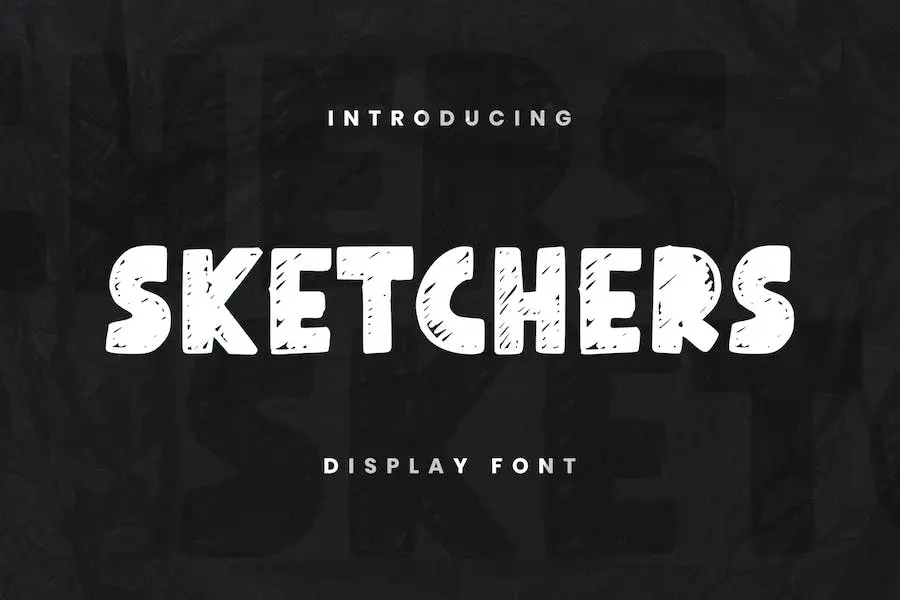
Sketchers 是一种名为“Presenting It”的字体,它提供了一系列功能和样式来增强您的设计项目。 该字体非常适合徽标、品牌、书籍、T 恤、杂志布局、问候语和标题,用途广泛,可适应各种设计需求。
借助大写和小写字母、数字和标点符号、多语言支持和 OpenType 功能,您有无数的选择来创建令人惊叹的设计。
另外,您还可以将其与其他字体混合以添加互补的感觉。 使用 Sketchers 为您的项目赋予独特且专业的外观。
特威克
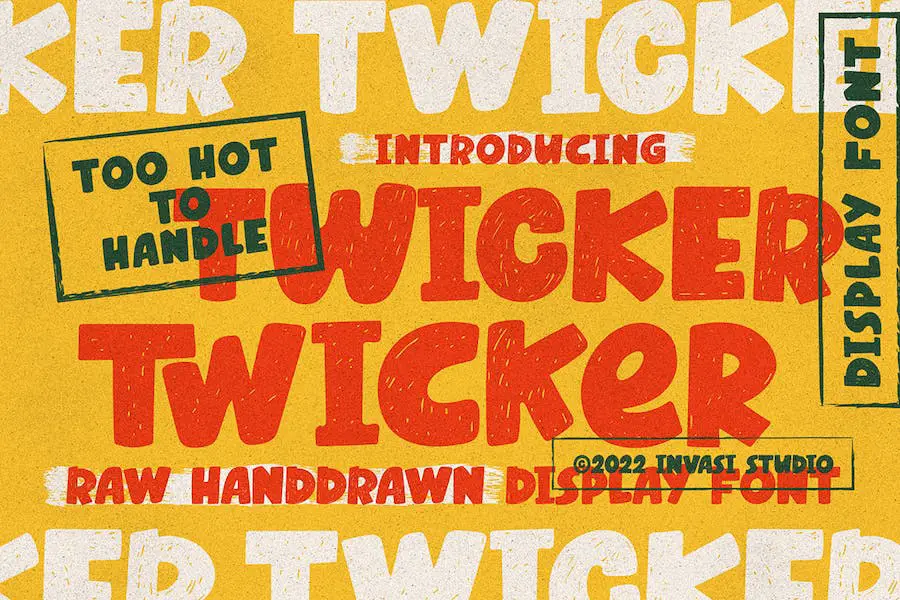
Twicker 是一种具有有趣的草图、纹理和垃圾阴影风格的字体。 其细节字形以迷人的气泡形状出现,赋予其独特的手绘外观,极具吸引力。
凭借各种替代字形和连字,您有很多选项来自定义您的项目。 无论是品牌项目还是包装,Twicker 都是增添俏皮感的完美选择。
粉笔时间
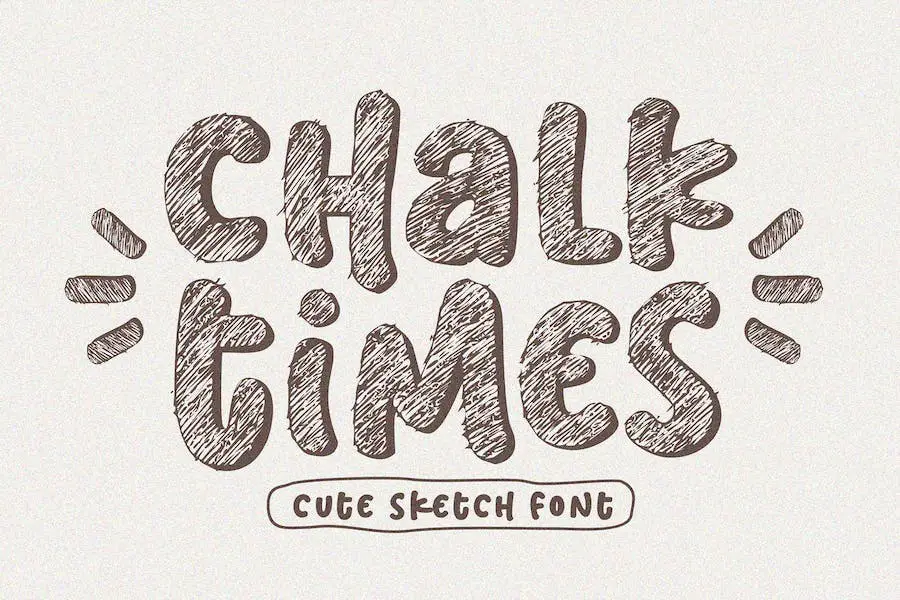
Chalk Times 是一种可爱、活泼、友好的轮廓显示字体,具有铅笔素描风格。 其自然而独特的设计使其非常适合各种项目。 通过 Chalk Times,您可以享受乐趣并探索这种美丽字体的无限可能性。
草图
Sketchup 是一种令人难以置信的字体,它将把您的设计提升到一个新的水平。 凭借其独特的草图显示板风格,它可以为您的徽标、标题、海报、徽章、T 恤等增添一抹个性。
受到装饰艺术和建筑运动的启发,这种字体为您的项目带来了美丽而有趣的元素。
无论您是要创建证书、帖子、徽标、海报、标签还是其他任何内容,Sketchup 都是让您的设计脱颖而出的完美选择。
艾洛迪
Elodie 是一种全大写字体,具有独特而古怪的字符。 该字体是使用毛笔创建的,给人一种手写和有机的感觉。 它非常适合标题、简短引言、产品名称等。
要为常规文本添加一丝奇思妙想,只需使用小写字母即可。 但如果您想让您的写作更加特别,请利用大写部分来实现那些独一无二的怪癖。
此外,Elodie 还为多种语言提供多语言支持,包括西欧、中欧和东欧语言。
素描手绘
Sketch Hand Drawn 是一款有趣的原创手写字体,能够让任何 DIY 项目变得栩栩如生。 凭借其华丽而独特的设计,这种字体非常适合希望为其项目添加个人风格的图形设计师。
无论您是在制作海报、徽标还是网站,素描手绘都一定会增强整体设计并使其脱颖而出。 其手工制作的外观增添了一种真实感和创造力,为您的作品带来独一无二的魅力。
使用 Sketch Hand Drawn 字体给您的项目带来新鲜和艺术的感觉。
萨利塔素描
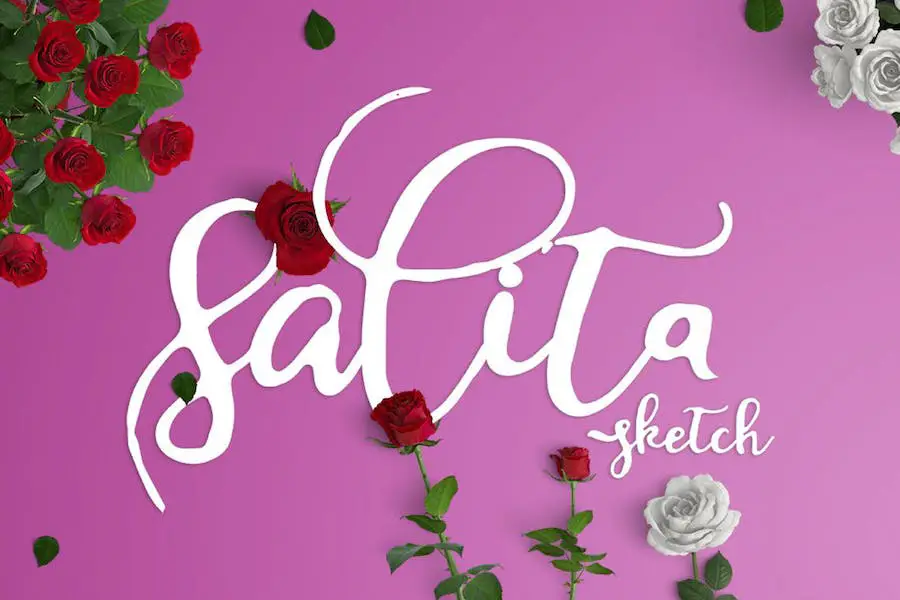
Salita Sketch 是一种为您的设计项目带来新鲜和现代气息的字体。 该字体拥有超过 340 个字形,提供了广泛的替代字符,包括花体和风格集,为您提供了大量的选项来增强您的设计。
Salita Sketch 的独特之处在于其手工书法风格和装饰字符,为您的作品增添优雅和俏皮的元素。
粉笔素描
Chalk Sketch 是一款很棒的显示字体,可为任何针对儿童的设计增添创意。 它用途广泛,可用于各种项目,如品牌、标志设计、T 恤、书籍封面等。
这种字体非常适合社交媒体帖子、广告、产品包装、标签、邀请函、文具以及您能想到的任何其他内容! 使用 Chalk Sketch 为您的项目添加独特而有趣的风格。
字母素描
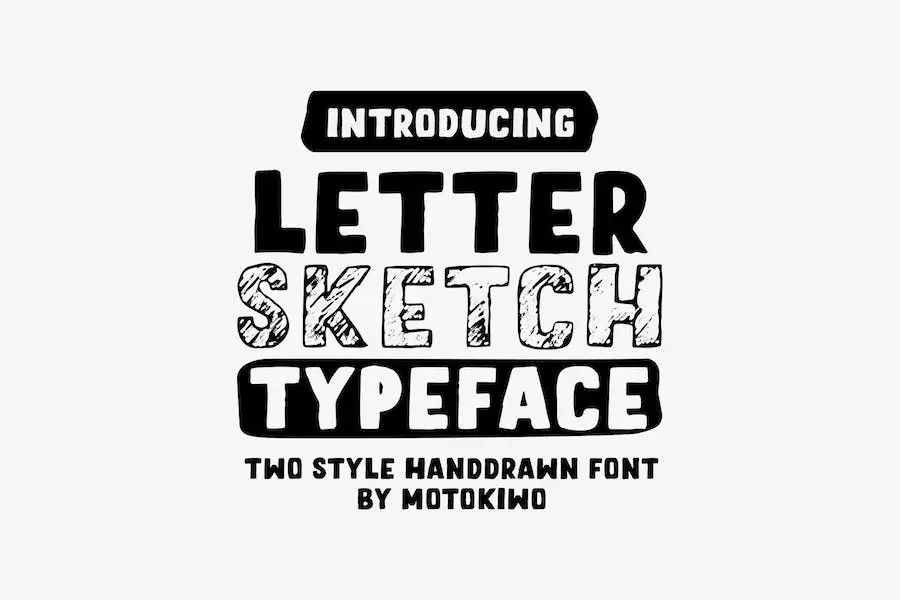
Letter Sketch 是一款出色的字体,可为您的引言、标语或标题增添有趣和独特的风格。 它采用全大写字母的手绘设计,有两种风格:粗略的草图和填充版本。
凭借其自然的绘画感觉,这种字体为您正在处理的任何项目增添了个人风格。 那么,为什么不使用 Letter Sketch 为您的设计增添一点额外的风格呢?
真实素描
Truesketch 是一款出色的字体,可为任何图形设计项目增添创意和独特性。 它不仅仅是普通字体——它是一种多功能工具,可用于各种数字项目。
该字体具有常规和斜体两种样式,可让您轻松地将真实的手写风格带入您的设计中。
Truesketch 的突出特点之一是它为每个字母提供了广泛的风格选择。 这意味着在强调文本的手写感觉时,您有多种选择可供选择。
最佳免费素描字体
希望为您的设计项目增添创意? 我们精心挑选的最佳免费草图字体就是您的最佳选择! 不要错过这些令人惊叹的选项,将您的设计提升到一个新的水平。
草图
Sketch 是一种非常适合希望增强项目设计的图形设计师的字体。 该字体由 DCoxy 和 Greg Medina 创建,可为任何设计增添独特的风格。 借助 Sketch,您可以凭借其有趣和艺术的属性将您的项目变为现实。
该字体的手绘外观赋予其个人风格,并为您的设计增添一丝奇思妙想。 Sketch 用途广泛,可用于各种项目,例如徽标、海报和包装。
对于希望为自己的作品添加独特和创意元素的设计师来说,这是必备的。
草图
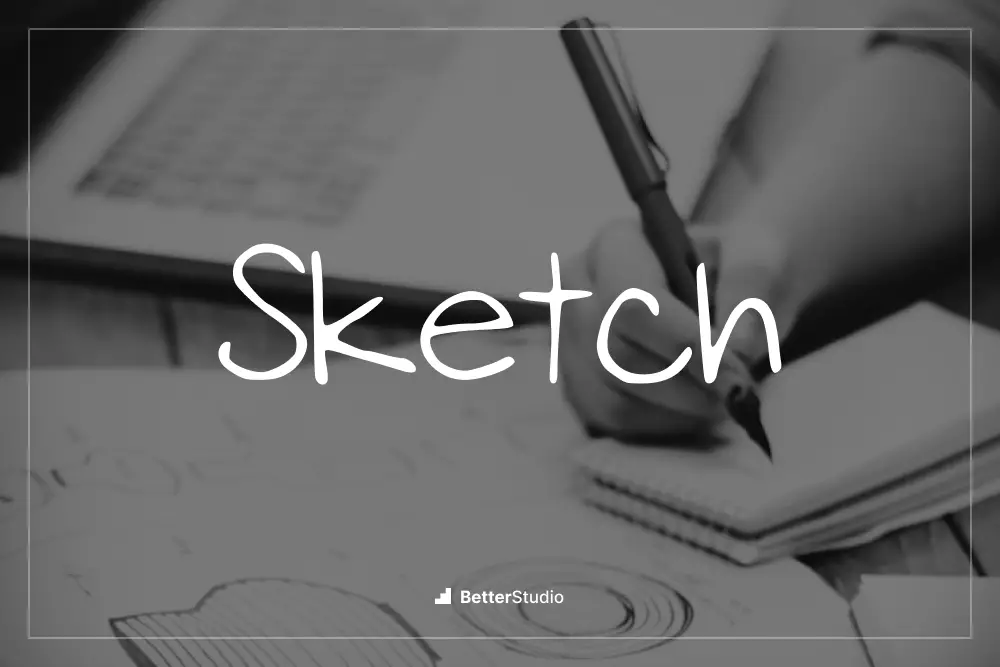
Sketch 是一种非常适合希望增强项目设计的图形设计师的字体。 这种独特的字体由 Kelsey Dugard 创建,提供了一系列属性,可以将您的设计提升到一个新的水平。
通过 Sketch,您可以使用各种独特且引人注目的字体。 每个角色都经过精心制作,以捕捉手绘美学,为您的设计增添一丝个性和魅力。
无论您是在制作徽标、海报还是网站,这种字体都会带来艺术气息。
粗略的草图
Rough Sketch 是 javapep 创建的一种字体,非常适合希望增强项目设计的图形设计师。 这种独特的字体增添了一丝个性和创造力,使任何设计脱颖而出。
凭借其粗犷的手绘风格,它为任何项目带来了个性化和艺术感。 粗略草图的关键属性之一是它的多功能性。 它可用于各种设计项目,从徽标和品牌到海报和社交媒体图形。
其粗糙的边缘和素描般的外观为设计增添了真实感和独特感,使其具有视觉吸引力。
客舱素描
Cabin Sketch 由 Pablo Impallari 设计,是一种独特的字体,可以极大地增强您的项目设计。 凭借其手绘风格,它为任何文本或徽标增添了个人和艺术气息。
这种字体具有一些突出的属性,使其成为图形设计师的绝佳选择。 首先,粗略且不均匀的线条赋予其原始和有机的感觉,使其非常适合需要手工美感的设计。
其次,广泛的字符和字形允许多功能和创造性的排版。 无论您是设计徽标、海报还是网站,Cabin Sketch 都提供了大量选项,让您的文字脱颖而出。
任抹素描
Dumadistyle 的 Jember Sketch 是一种独特的字体,非常适合希望增强其项目的图形设计师。 这种字体为任何设计增添了个人风格,赋予其更具艺术感和手绘感。
使用 Jember Sketch,您可以将您的设计提升到一个新的水平。 这种字体具有类似草图的品质,可以为您的项目增添深度和特色。 它非常适合创建徽标、海报、邀请函等。
Jember Sketch 的突出特点之一是它的多功能性。 这种字体可用于各种设计风格,从复古风格到现代风格。 其手绘外观增添了一种真实感和魅力,将吸引您的观众。
经常问的问题
草图字体是旨在模仿手绘或类似草图的字体的字体。 它们为任何设计项目增添了独特的艺术气息,无论是徽标、海报还是网站。
这些字体通常具有不均匀的线条、有趣的缺陷和手工制作的感觉,为您的文本带来个性和魅力。
使用草图字体可以给您的设计带来更具创意和异想天开的氛围。 它们可以使您的文字脱颖而出并唤起艺术表达感。
草图字体非常适合为与艺术、工艺品、时尚或任何需要有趣和非正式风格相关的项目添加手工制作的感觉。 它们可以为您的设计增添个性和视觉趣味,帮助您的设计更令人难忘、更具吸引力。
结论
总之,我们讨论了 2023 年 15 种最佳草图字体,包括免费和高级选项。 这些字体可以极大地增强您的项目设计,并赋予它们独特和创造性的触感。
无论您是图形设计师还是希望提高作品视觉吸引力的人,这些字体绝对值得探索。